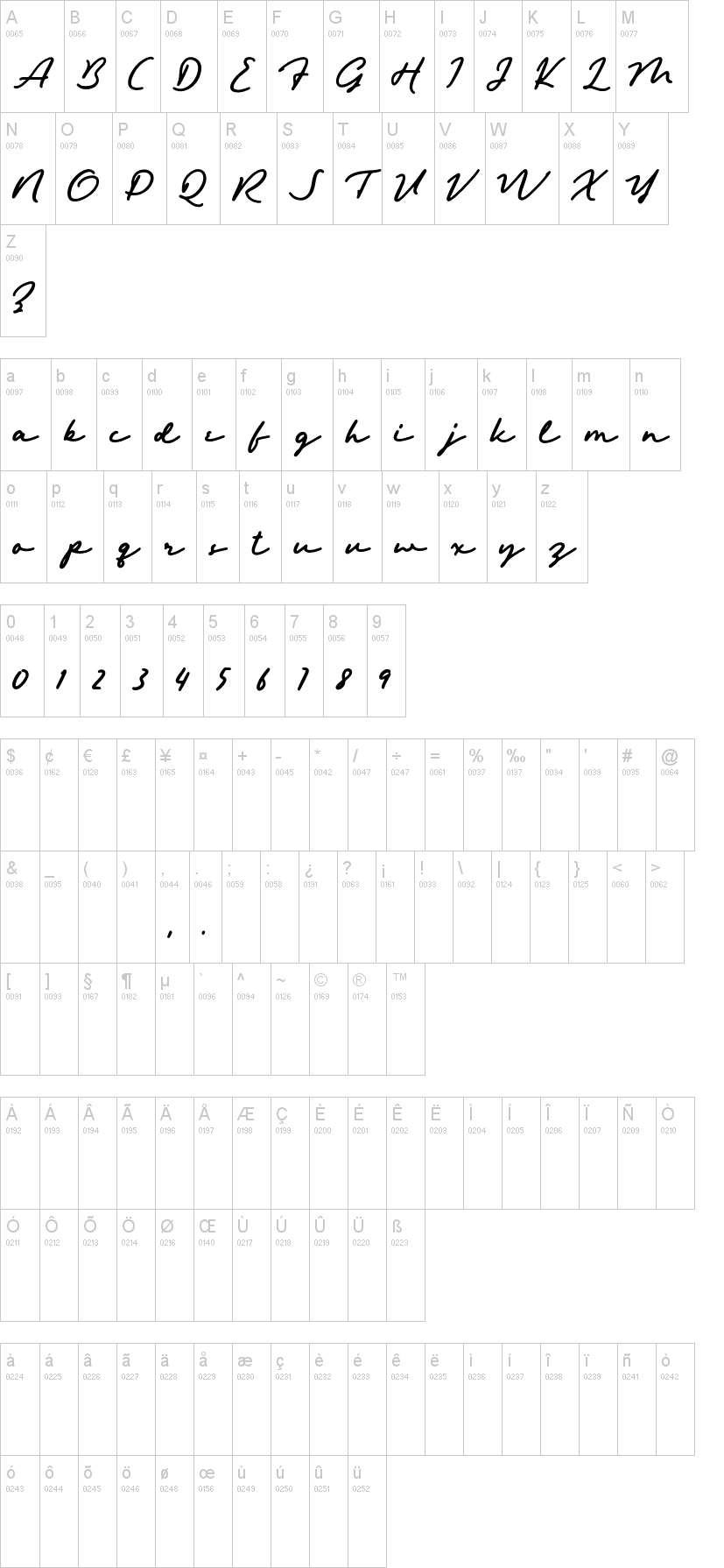
Hemisphers Script
Hemispheres Script 是一种手写风格的字体,它的设计灵感源于传统的手写书法艺术。这种字体的特点是流畅、优美,具有独特的个性和风格,并且能够充分表现出手写艺术所具有的温暖和人情味道。 Hemispheres Script 字体的笔画流畅而自然,每个字母之间的连结都非常顺畅。它的字形较为修长,但是并不会让人感到过于紧凑或拥挤。同时,这种字体还采用了一些细小的装饰和笔画,以增强其视觉吸引力和艺术感。 由于 Hemispheres Script 字体的优雅和舒适的手写风格,它常被用于一些需要表达轻盈、舒适、温馨等情感的设计场景,例如婚礼请柬、手写信件、文艺风格的海报等等。
Hemisphers Script是一款非常不错的手写艺术字体,具有很好的视觉感,适合于文化类的宣传设计、商业类品牌的广告和产品包装设计以及个性化文字排版等较多场景。